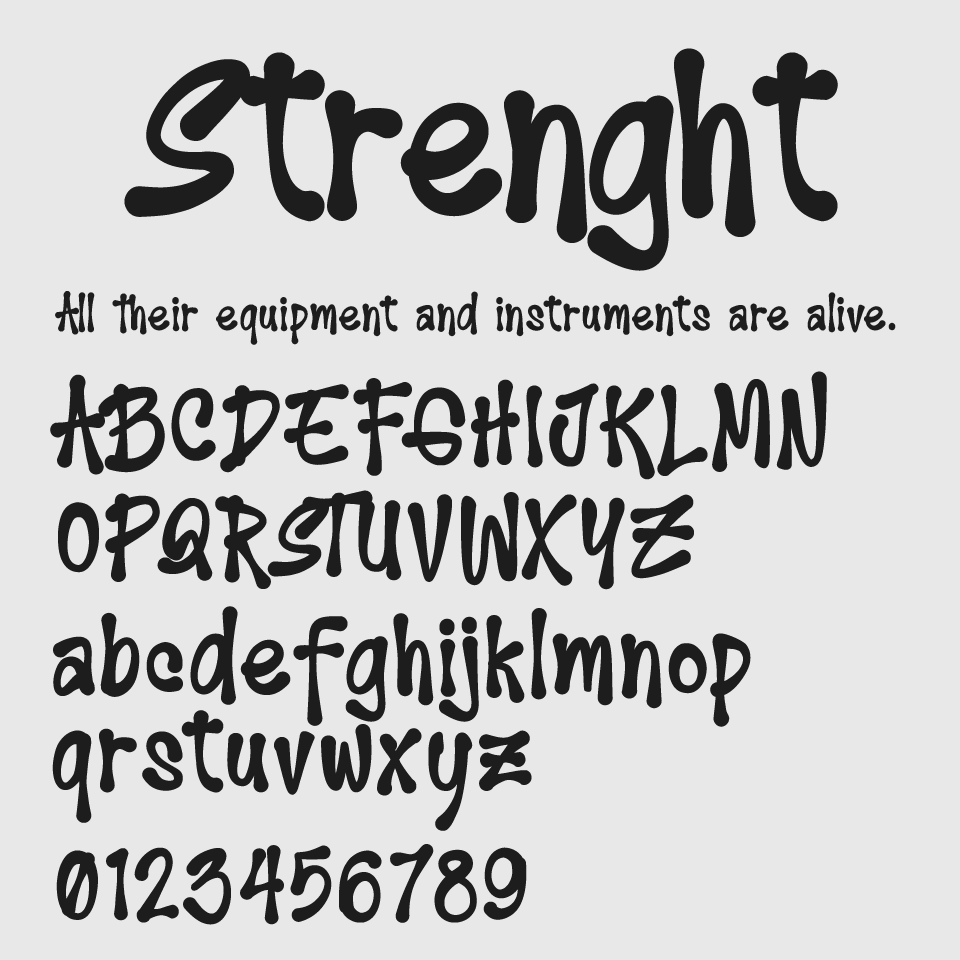
Strenght to Strenghtフォントは、手書きの温もりとゆるさが漂う親しみやすいグラフィティな手書きフォントです。
太めなブラシやスプレーなどで書かれた質感をもち、文字ごとの太さや傾きに微妙な揺らぎがあり、無邪気でラフな雰囲気のあるフォントです。縦長のフォルムでありながら、グラフィティやスケートボードなどを愛しているストリート系にぴったりなフォントです。